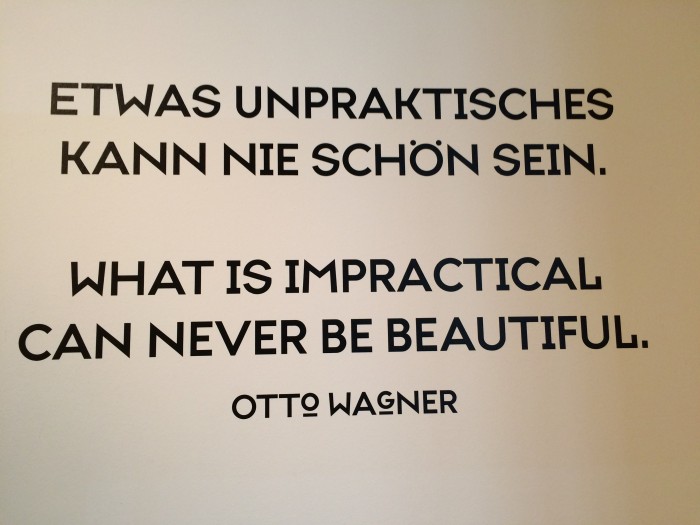
Beschriftung in Österr. Postsparkasse in Wien (Otto Wagner-Bau)
Vielleicht kann mir hier jemand helfen um welche Schrift es sich handelt?
Gelöst von StefanB
Wobei man sich bei dem gezeigten Beispiel die Frage stellen kann, ob der verwendete Font und Versalsatz schön oder unpraktisch ist ...
Ich finds schlimm ...
ja. noch dazu ist ja die postsparkasse ein herrliches beispiel des jugendstils. das hat mit (dem von mir verehrten) brody nicht viel zu tun.
Die denkmalschutzgerechte Renovierung dieses Gebäudes hat ein befreundeter Architekt gemacht. Ich müsste ihn direkt mal fragen, wer für die Schriftauswahl im Museumsshop (denn da steht dieser Satz in einem Nebenraum) verantwortlich war.
Ich weiß - ich war beim meinem letzten Wienbesuch vor sieben oder acht Jahren dort. Tolles Gebäude.